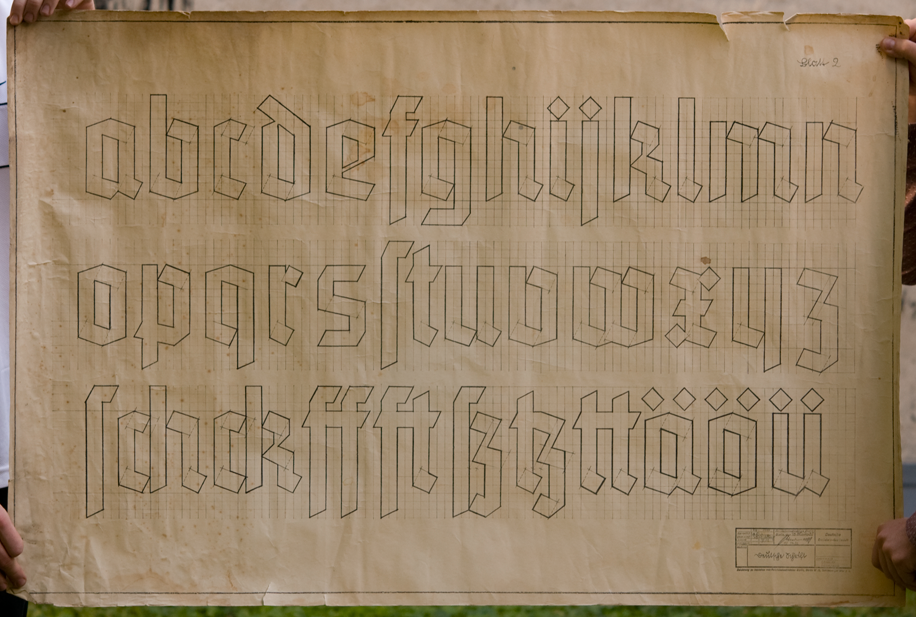
Typo-Geschichte interpretiert: Eine Auseinandersetzung mit Schrift im öffentlichen Raum
In erster Linie dient ein Navigationssystem die Orientierung ihrer Nutzer. Auch im Berliner S-Bahn-Netz sollten die Schilder bei der Wegfindung helfen. Kritiker sehen einige der dortigen Schriften als behaftet. Gibt es „gefährliche Schriften“? Selbst Entwürfe, die für viele Designer als neutral wirken, können eine politische Ideologie verkörpert haben, z. B. eine sozialistische, kapitalistische oder faschistische. Im Laufe der Projektwoche werden die Studierenden Kurztexte über die Geschichte eine dieser Schriften und die Debatten darüber, lesen und diskutieren. Anschließend werden Kursteilnehmer sich anhand ihrer eigenen Fotografien oder Zeichnungen mit einer Schrift auseinandersetzen, in Form eines Plakates oder eines Büchleins. Bringt eine Kamera und ein Skizzenbuch zur ersten Veranstaltung bitte mit!
A note on blackletter classification (in English)
Many German typographers list four blackletter varieties – Textura, Rotunda, Schwabacher, and Fraktur. Some add a fifth class, often called Fraktur-Varianten, which is a catch-all place to put everything else. While many contemporary blackletter type designs fall into that last group, type designers continue to revive styles across the rest of the spectrum as well. Understanding blackletter classification helps you choose the right typeface. For example, a German Fraktur would be a poor choice for an English Pub. On the other hand, almost any of the above styles could look right on a certificate, depending on its overall design.
Old English and Gotisch designs are further evolutions of the Textura idea. Gotisch (meaning “gothic”) alone has several sub-styles, from the nineteenth century romanticist fette Gotisch – pictured above in the third slot down in the first column on the left – to schlichte Gotisch, the so-called Schaftstiefelgrotesk, or “jackboot grotesques” of the 1930s. Indeed, it is this last genre of Texturas that we will engage with in this course.
Schwabacher is the style of Bastarda that has traditionally been used in Germany the most often. Fraktur itself could even be classified as another Bastarda – but I have given it its own group above, as it was the most-widely used blackletter text style in German typography between the early 1500s and the early 1940s. Evolving out of late medieval and early renaissance handwriting, the various blackletter styles also influenced each other over time. Another Bastarda genre, Civilité, was common in late sixteenth century printing in France and the Low Countries.
Since at least the late eighteenth century, there have also been “experimental” blackletter varieties, which are difficult to sort using twentieth-century group definitions. One of them, pictured above in the right-most column, is the class of hybrid blackletter/roman typefaces. You can read more about those typefaces here.
Schlichte Gotisch oder Schaftstiefelgrotesk?
Wie herausfordernd häßlich sind dagegen die Ortsschilder auf fast jedem einzelnen deutschen Bahnhof! Nur die seltenen antiken Beschriftungen aus der Zeit vor 1880 sind in ihrer Art schön. Selbst wo die dort verfehlte und ohnehin nicht gerade anmutige, in Schaftstiefeln marschierende Kochschrift und die pseudogotischen Ortsschilder aus der trübsten Zeit der neueren Geschichte verschwunden sind, läßt die Form dieser wichtigen Tafeln, die doch Visitenkarten des ganzen Landes sind, alle zu wünschen übrig.
Aus: Jan Tschichold, Erfreuliche Drucksachen durch gute Typographie. Maroverlag, Augsburg 2001 (ursprünglich: Ravensburger Buchverlag 1960), S. 20
Archivale
Originalvorlagen einer Schrift, die vermutlich für Schilder der Reichsbahn entworfen war.
- Deutsche Reichsbahn-Gesellschaft: Deutsche Schrift, gezeichnet von einem Herrn oder eine Frau »Friedling« am 7., 9. und 10. Mai 1935. Drei Blätter. Reichsbahndirektion Berlin 1935. Privatbesitz Lars Krüger, Berlin
Diese »Reichsbahnschift« ist die halbfette Element ziemlich nah. Die Element wurde von Max Bittrof entworfen und von die Bauersche Gießerei in Frankfurt am Main 1933 veröffentlicht. Es gibt im Berliner S-Bahn-Netz außerdem noch einige Schilder, die mit der Tannenberg gemacht sind. Die Tannenberg stammt von Erich Meyer; D. Stempel AG in Frankfurt am Main hat diese Schrift vertrieben.